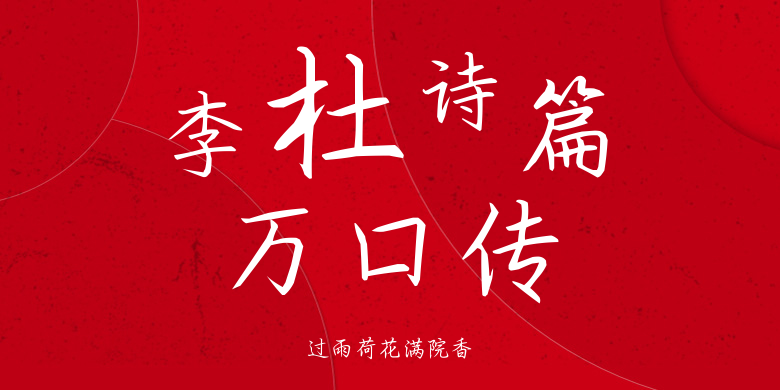
过雨荷花满院香
过雨荷花满院香,这款字体结构工整、笔画清晰,兼顾美观与易读性,适用于标题、正文、海报、包装、LOGO 等多种场景。字形优雅稳定,风格百搭耐看,适配日常排版与创意设计,让文字呈现更舒适、更具质感。过雨荷花满院香一笔一画,皆是细节,以均衡的比例、流畅的线条打造舒适视觉体验,字形端正大气,风格简约现代。无论是商业设计、品牌宣传还是日常排版,都能轻松驾驭,让文字更有格调与力量。过雨荷花满院香字体下载。